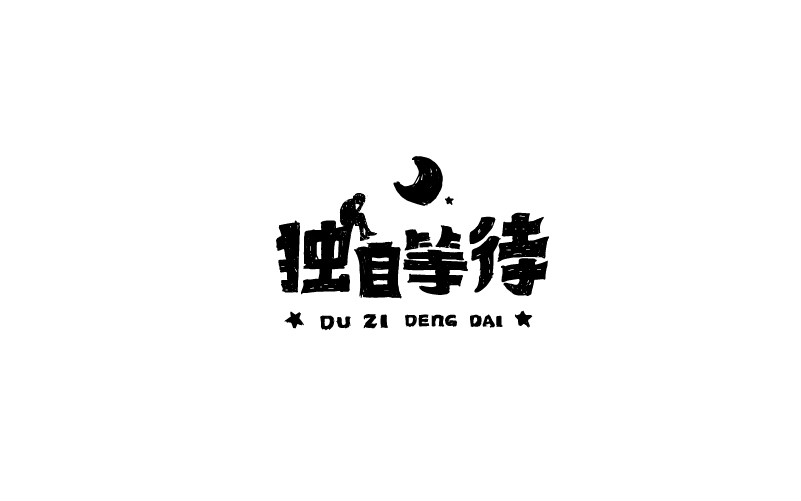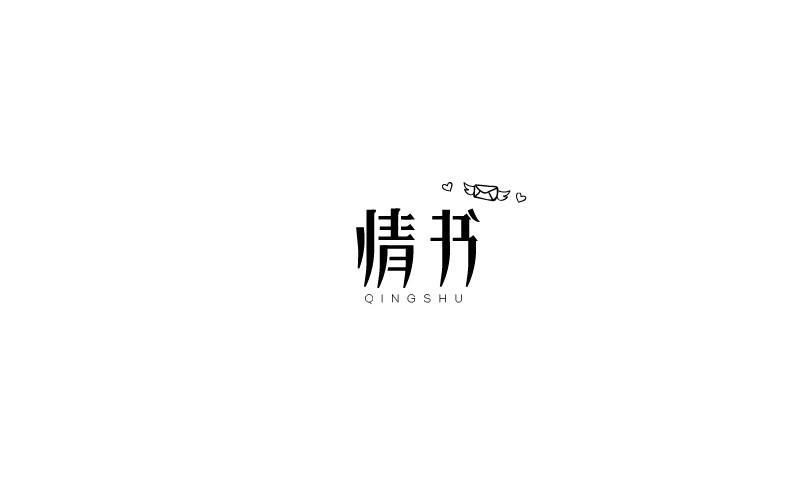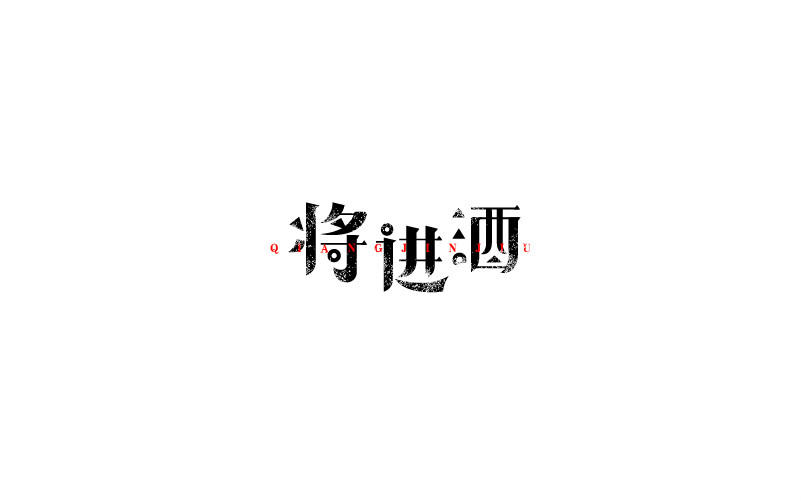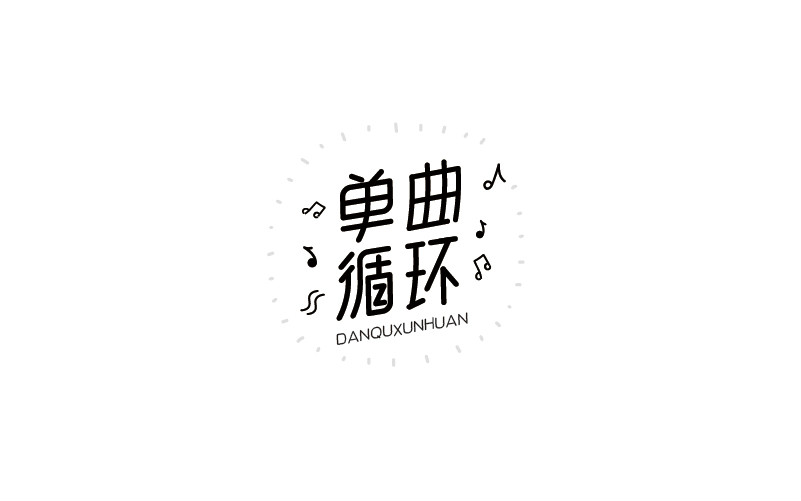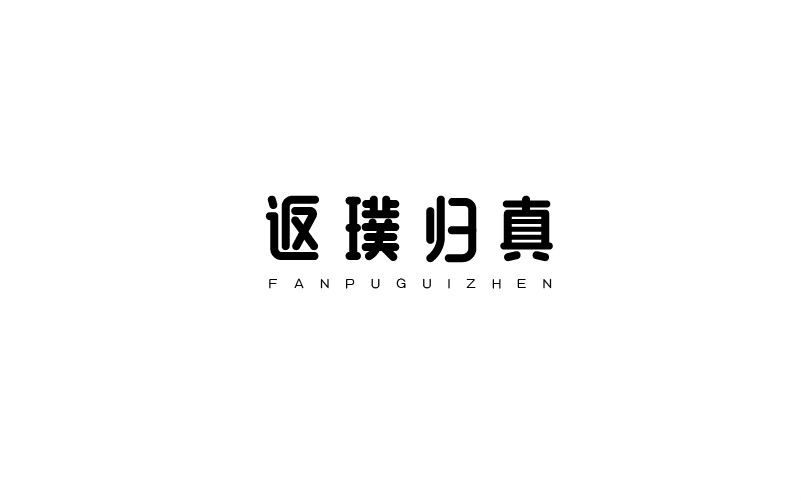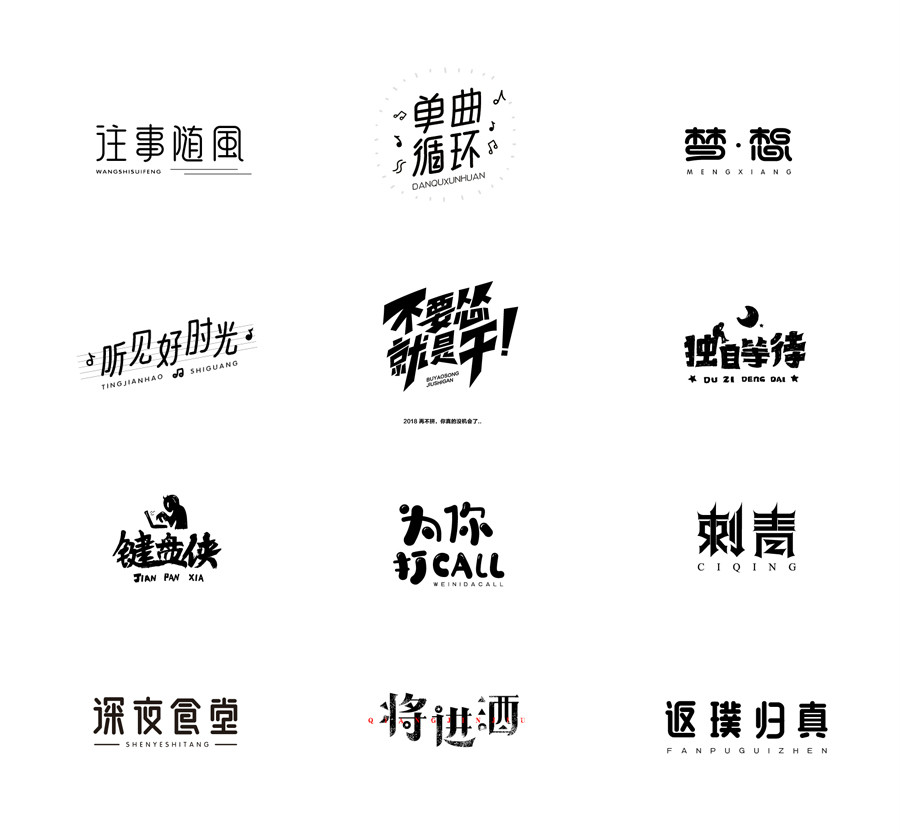
12款黑白字體設(shè)計,簡約藝術(shù)字體設(shè)計
設(shè)計師獨(dú)特的構(gòu)想加上適當(dāng)?shù)脑厝谌?,根?jù)文字的內(nèi)涵進(jìn)行設(shè)計。下面家佳樂文學(xué)小編為你帶12款黑白字體設(shè)計,簡約藝術(shù)字體設(shè)計。